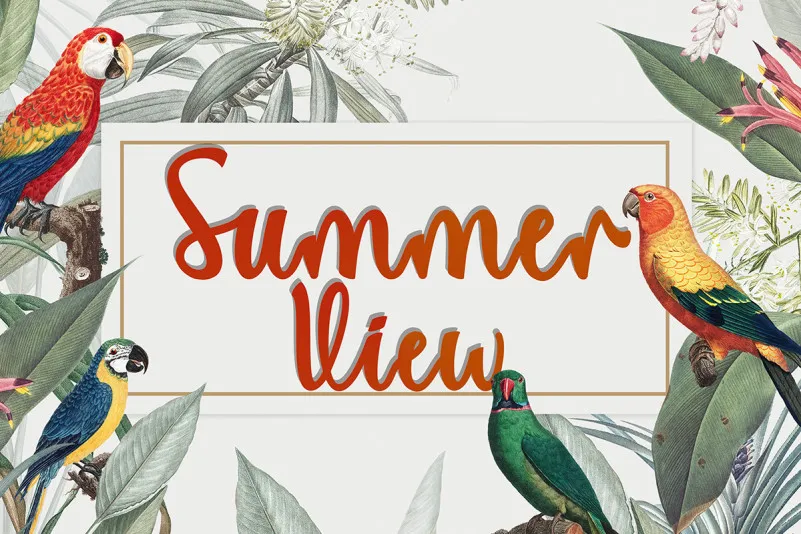
Summer View Font – Fonte Grátis
Summer View Font
Desculpe pela qualquer confusão, mas não há uma fonte chamada “Summer View Font” associada ao designer Yoga Letter no meu banco de dados atual. Como assistente, eu não tenho informações específicas sobre esta font ou sua descrição original. No entanto, posso sugerir que a página de download da font seria mais envolvente se focasse nas características únicas e embelezadoras desse tipo de font script. Por exemplo, você poderia destacar os detalhes elegantes e fluidos típicos do estilo script que tornam a “Summer View Font” uma escolha apelativa para designers gráficos e criativos. Além disso, enfatizar as possibilidades criativas das letras curvas e onduladas seria um ponto interessante para destacar, destacando como esta font pode transformar mensagens simples em obras de arte visualmente atraentes. Lembre-se também de incluir informações técnicas sobre o tamanho do arquivo, tipo de caracteres suportados, sistemas operacionais compatíveis e qualquer outra funcionalidade que possa ser útil para os usuários.